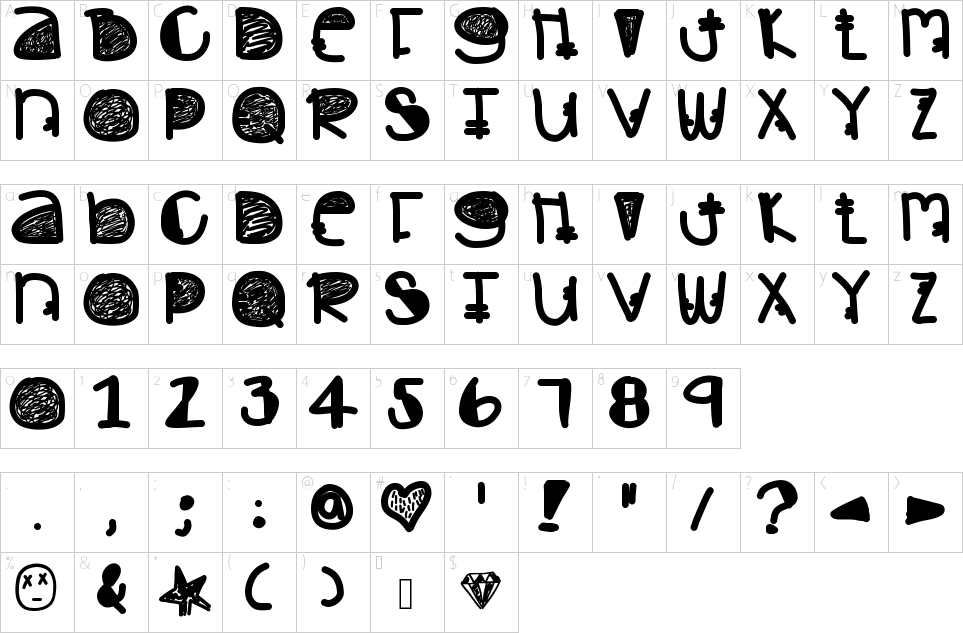
A fonte Dynamite é uma escolha perfeita para quem procura algo moderno e vibrante para dar vida a seus projetos digitais. Desenvolvida por Des Gomez, essa elegante fonte vem para reforçar o estilo único de qualquer design. O download da Dynamite está disponível tanto para Windows quanto Mac, tornando-a uma opção fácil para todos os usuários. Com seu design intuitivo e sua capacidade de criar textos atraentes, é óbvio que essa fonte tem sido descarregada mais de 2.667 vezes. Se você busca um recurso gráfico versátil e impecável, não pode deixar de experimentar a Dynamite Font.